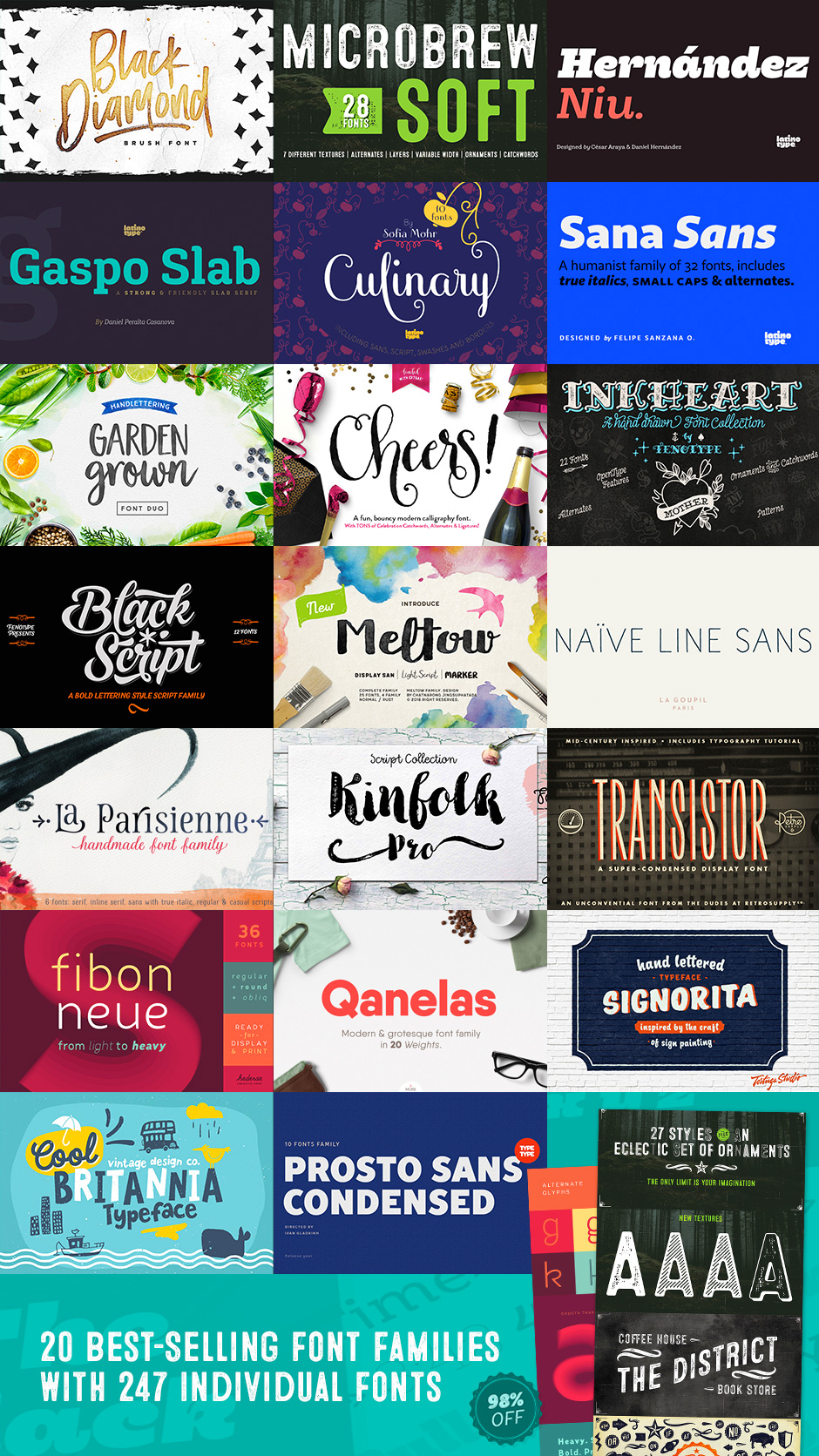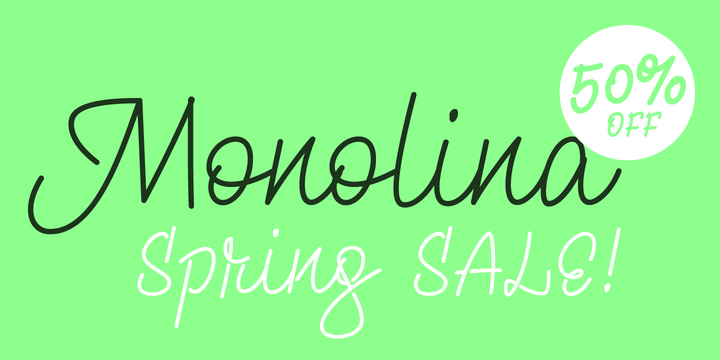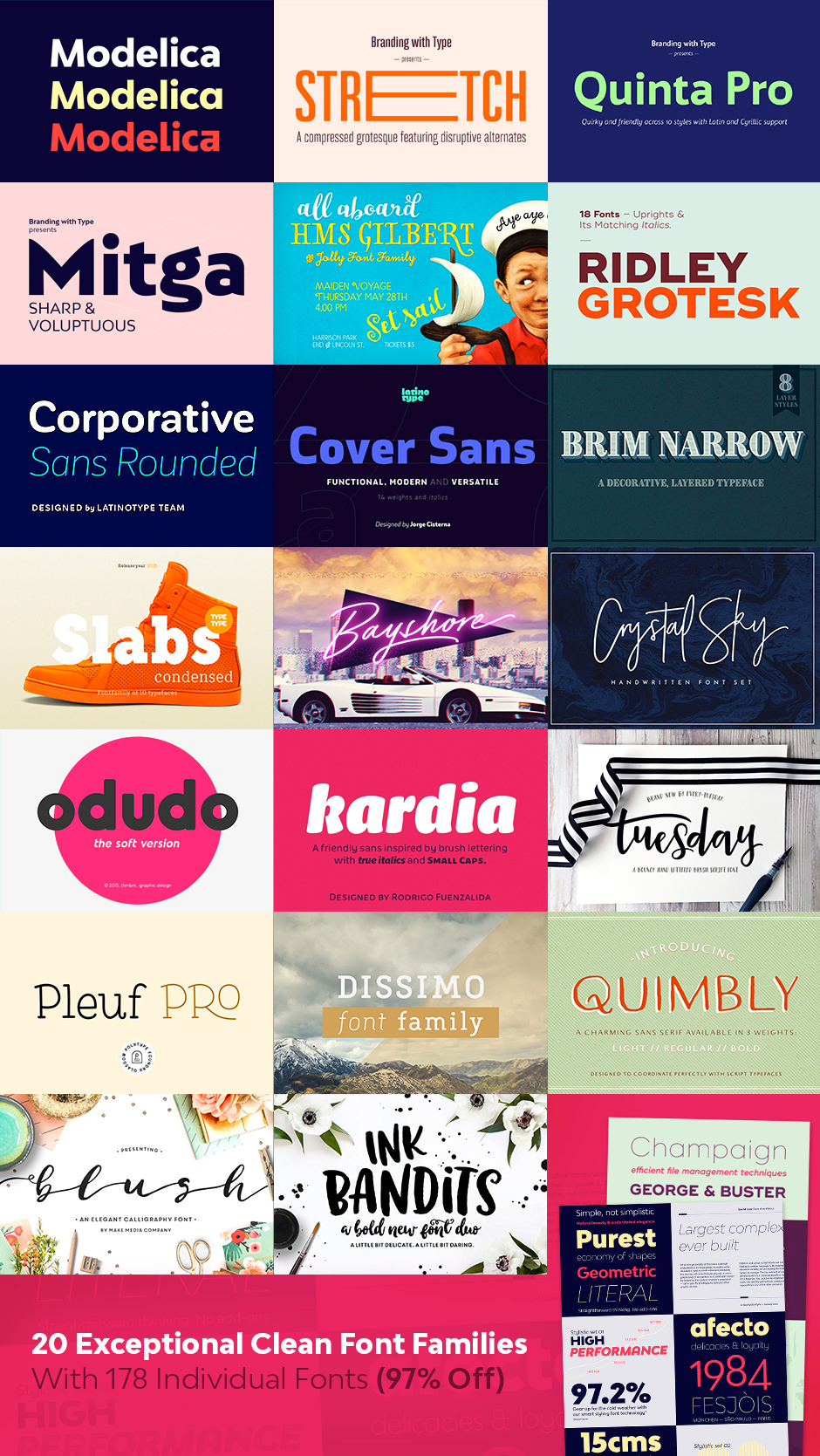
schon wieder so ein 20er-paket. um neunundzwanzig euro dollar!  :neenee:
sind ein paar eher schräge dabei, aber auch durchaus brauchbares. verschiedene foundries. was ich so beim ersten drüberschauen sehen konnte sind es diesmal nicht nur einzelschnitte sondern meist ganze familien.
(einige sogar mit versaleszett)
Die Monolina find ich ja ganz hübsch, aber ... wenn es doch bloß ein alternatives "r" gäbe :-( Mich wundert, dass es das nicht gibt, denn für viele andere Kleinbuchstaben gibt’s die. Schade.
Zur KNILE-Slab (@bertel)